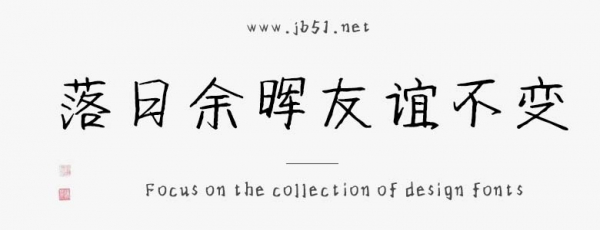
落日余暉友誼不變由字耕者字庫(kù)出品的字體,字體筆觸略細(xì),書(shū)寫(xiě)流暢,具有很好的視覺(jué)感,適合應(yīng)用于藝術(shù)設(shè)計(jì)、平面宣傳設(shè)計(jì)、網(wǎng)頁(yè)設(shè)計(jì),書(shū)法字帖等領(lǐng)域。有需要的朋友快來(lái)本站下載使用吧。